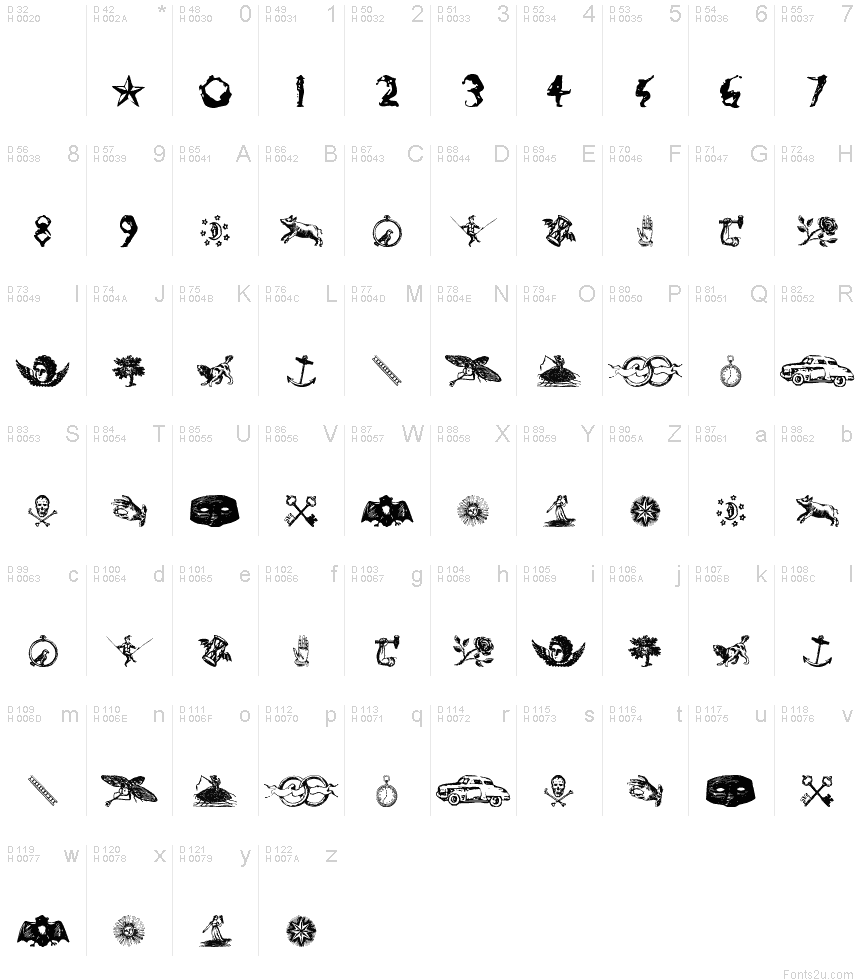
Infinite Dingbats von Shaun Kardinal ist eine kostenlose Fantasy-Dingbat-Schrift, die eine ganze Sammlung seltsamer, tintiger Relikte in Ihr Layout bringt. Geflügelte Putten, trompetenspielende Kobolde und gravierte Hände – sie alle teilen sich dieselbe kratzige Holzschnitt-Textur. Dadurch wirken selbst grundverschiedene Icons, als stammten sie aus ein und demselben verhexten viktorianischen Druck. Die Grafik hat einen rauen, fast staubigen Touch, der verhindert, dass alles zu sauber oder digital wirkt.
Mit Infinite Dingbats verleihen Sie Konzertplakaten, okkulten Grafiken oder Tarot-Motiven, Zines, Album-Covern, Stickern und experimentellen Buchgestaltungen im Handumdrehen eine besondere Atmosphäre. Die Icons kommen groß und fett am besten zur Geltung; kombinieren Sie sie mit einer einfachen Serif oder Sans-Serif, damit die Illustrationen im Mittelpunkt bleiben. Diese kostenlose Schrift ist perfekt für Designer, die schnelle, wirkungsvolle Bilder suchen, ohne nach separaten Vintage-Cliparts suchen zu müssen.
MCIS lyrics booklet artwork, made into a font by Shaun Kardinal.